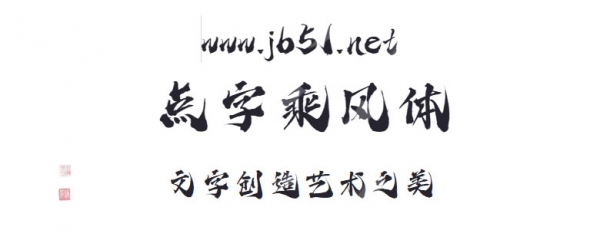
點(diǎn)字乘風(fēng)體是由點(diǎn)字庫推出的藝術(shù)字體,用筆沒有過分輕重,而是在結(jié)構(gòu)中強(qiáng)調(diào)“影漸疏”,書寫節(jié)奏起承轉(zhuǎn)合閑適自得,適合應(yīng)用于藝術(shù)設(shè)計(jì)、各類廣告和產(chǎn)品包裝設(shè)計(jì)等領(lǐng)域。